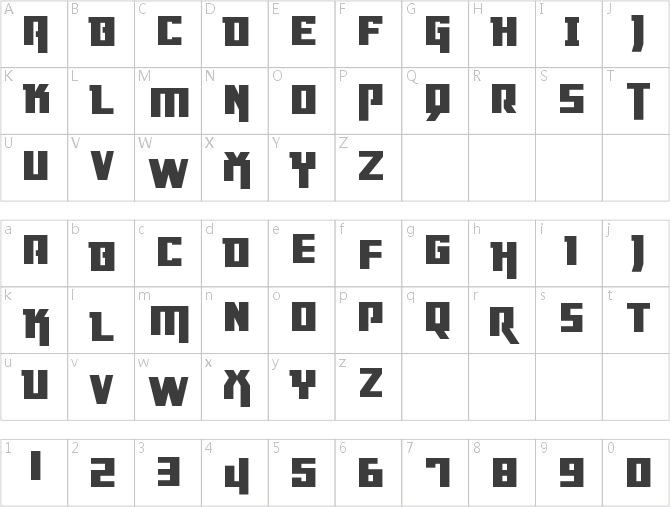
Danger Flight Expanded 詳情頁(yè)
Danger Flight Expanded字體字庫(kù)是一款讓人賞心悅目、百看不厭的英文字體,適合各類廣告和產(chǎn)品包裝設(shè)計(jì)應(yīng)用,字體大小0.02MB,格式為ttf字體,上傳用戶是多拉MO,作者/版權(quán)方為未知